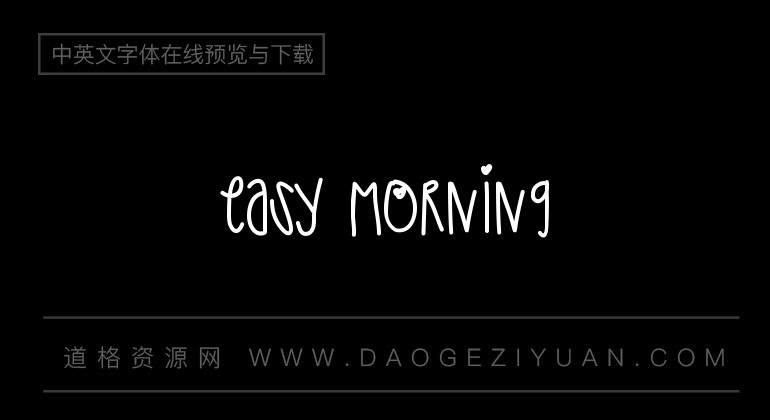
Easy Morning是一款清新自然的英文字体,由英国设计师Gemma O'Brien设计。它拥有细腻的线条,温柔的角度,柔和的气息,让人感觉清新而自然,十分适合用于婚礼邀请卡、海报、商业广告等。内容介绍
Easy Morning是一款非常不错的手写艺术字体,具有很好的视觉感,适合于文化类的宣传设计、商业类品牌的广告和产品包装设计以及个性化文字排版等较多场景。